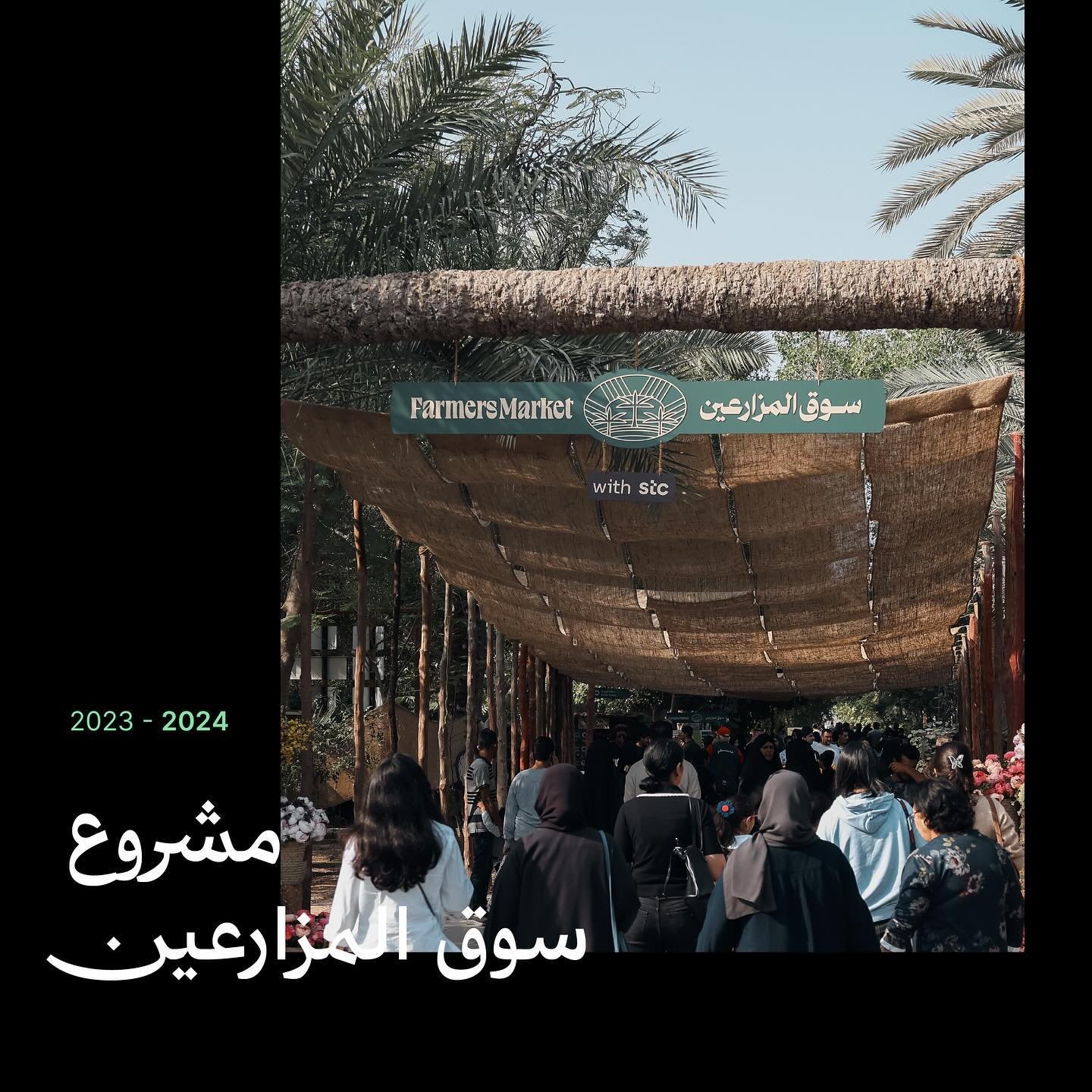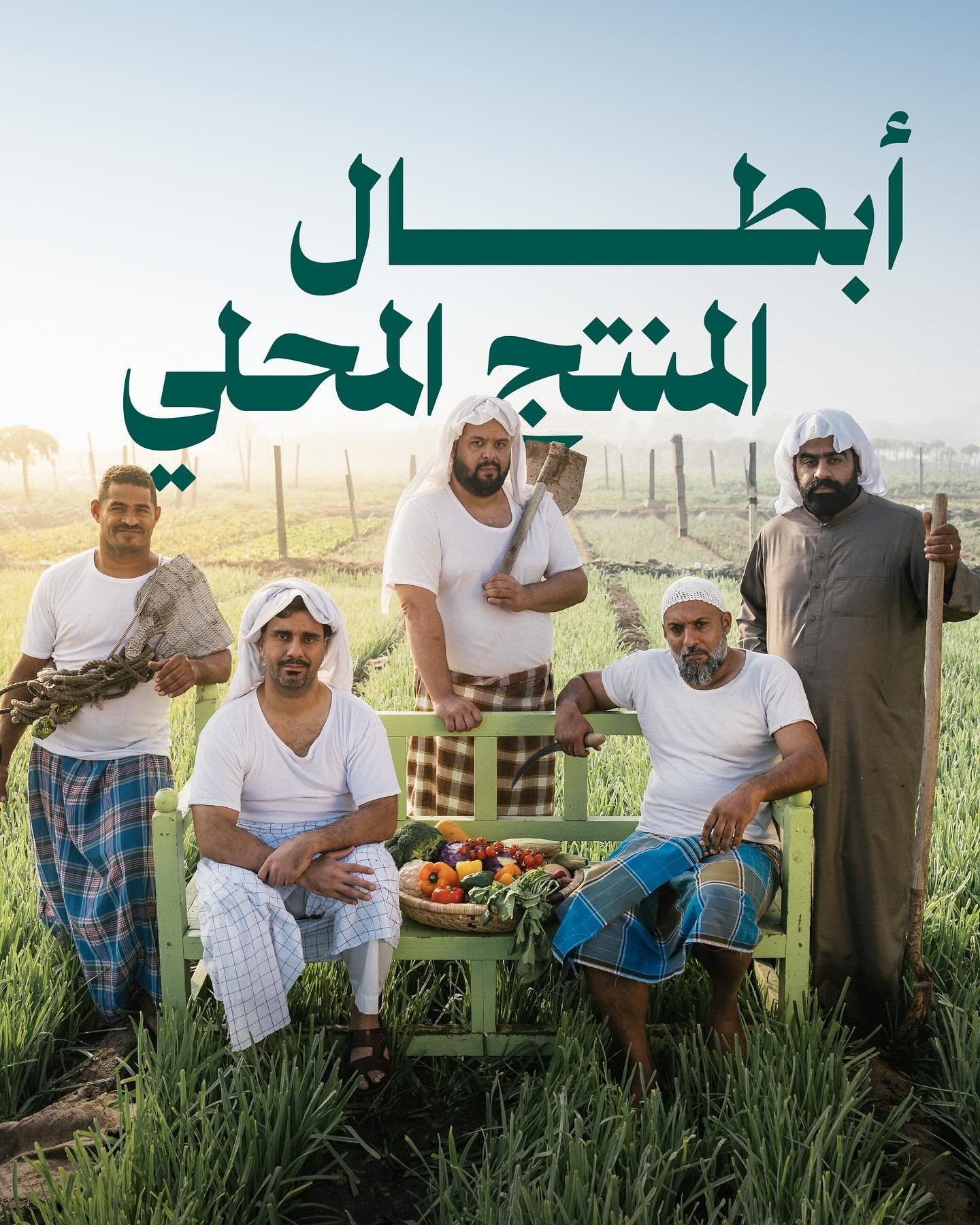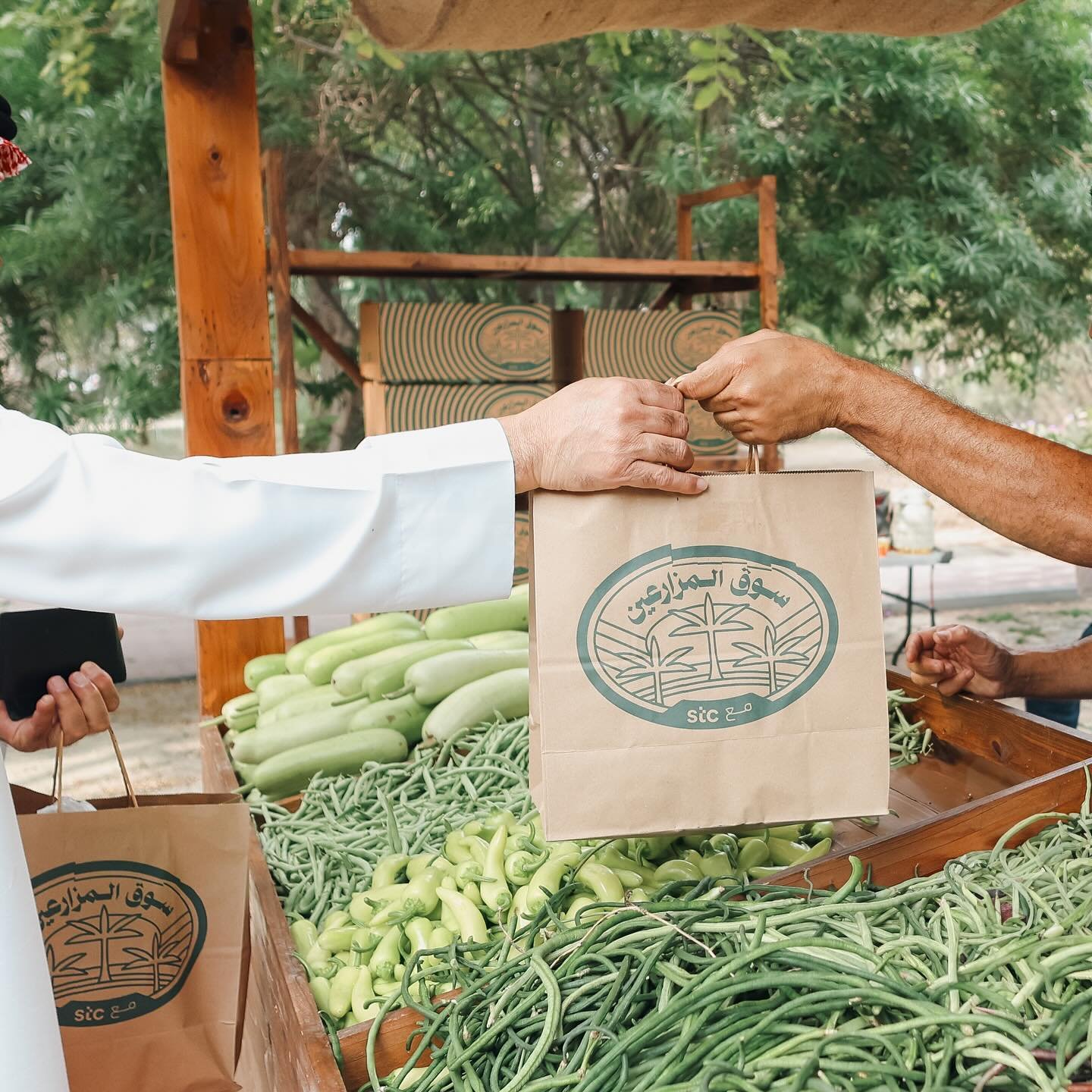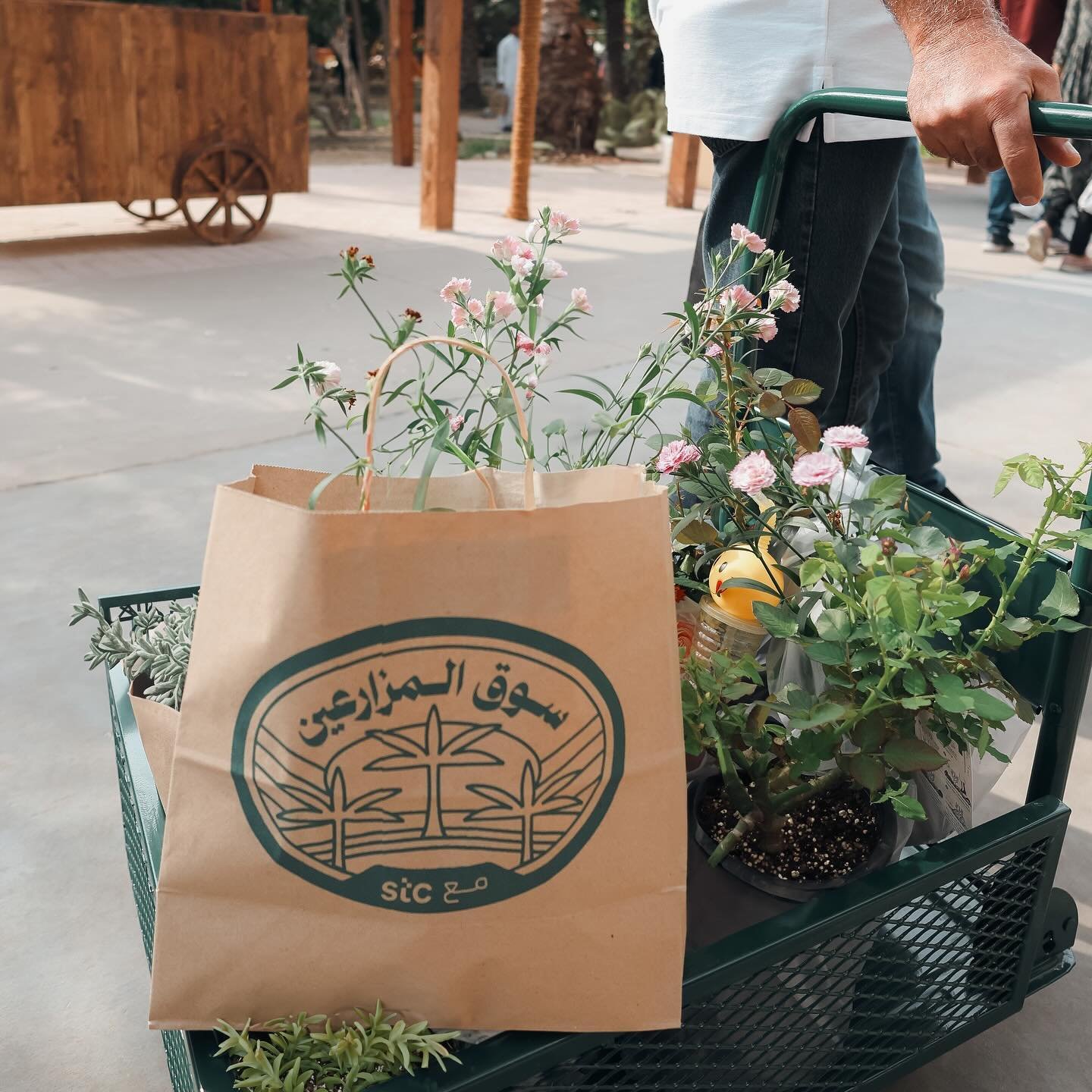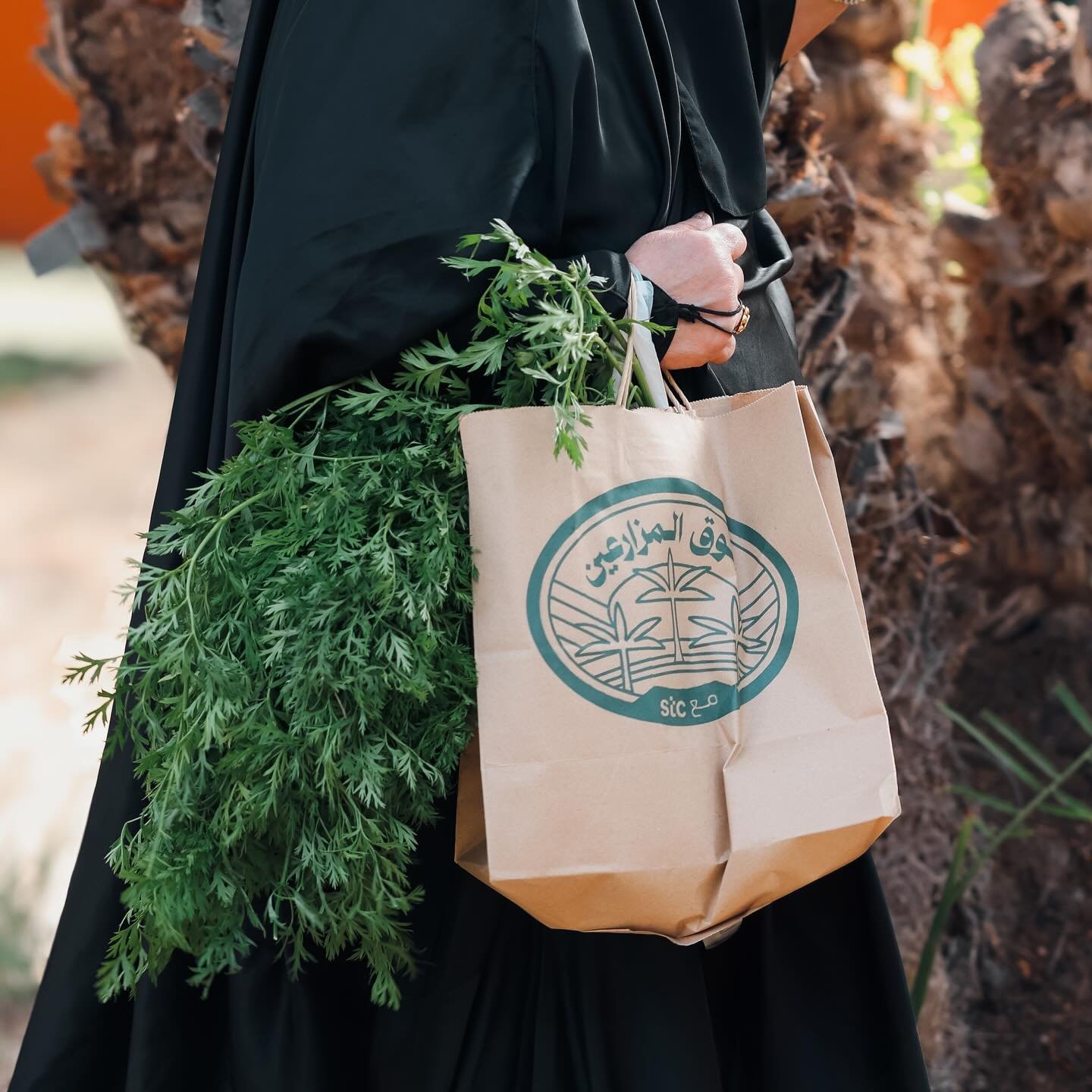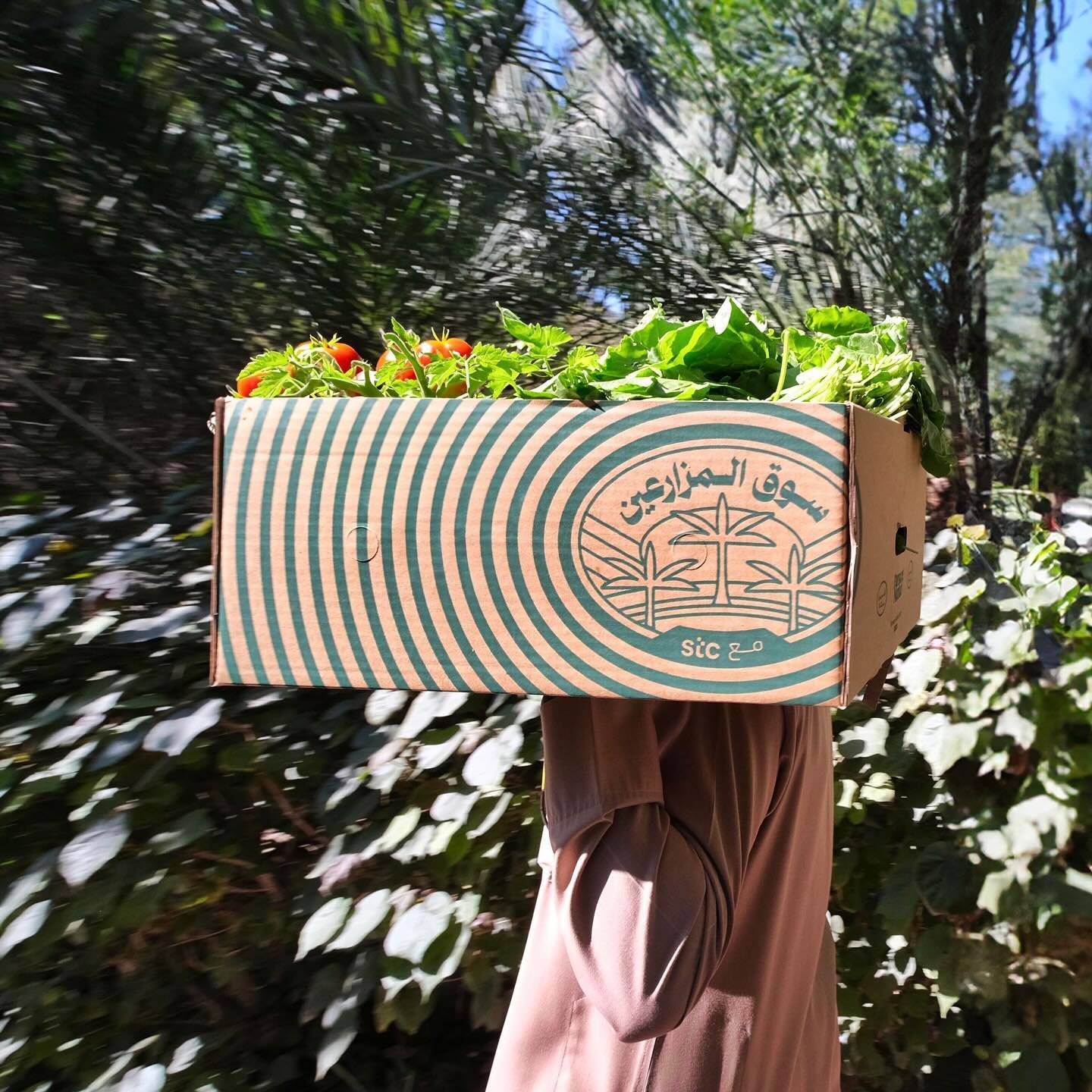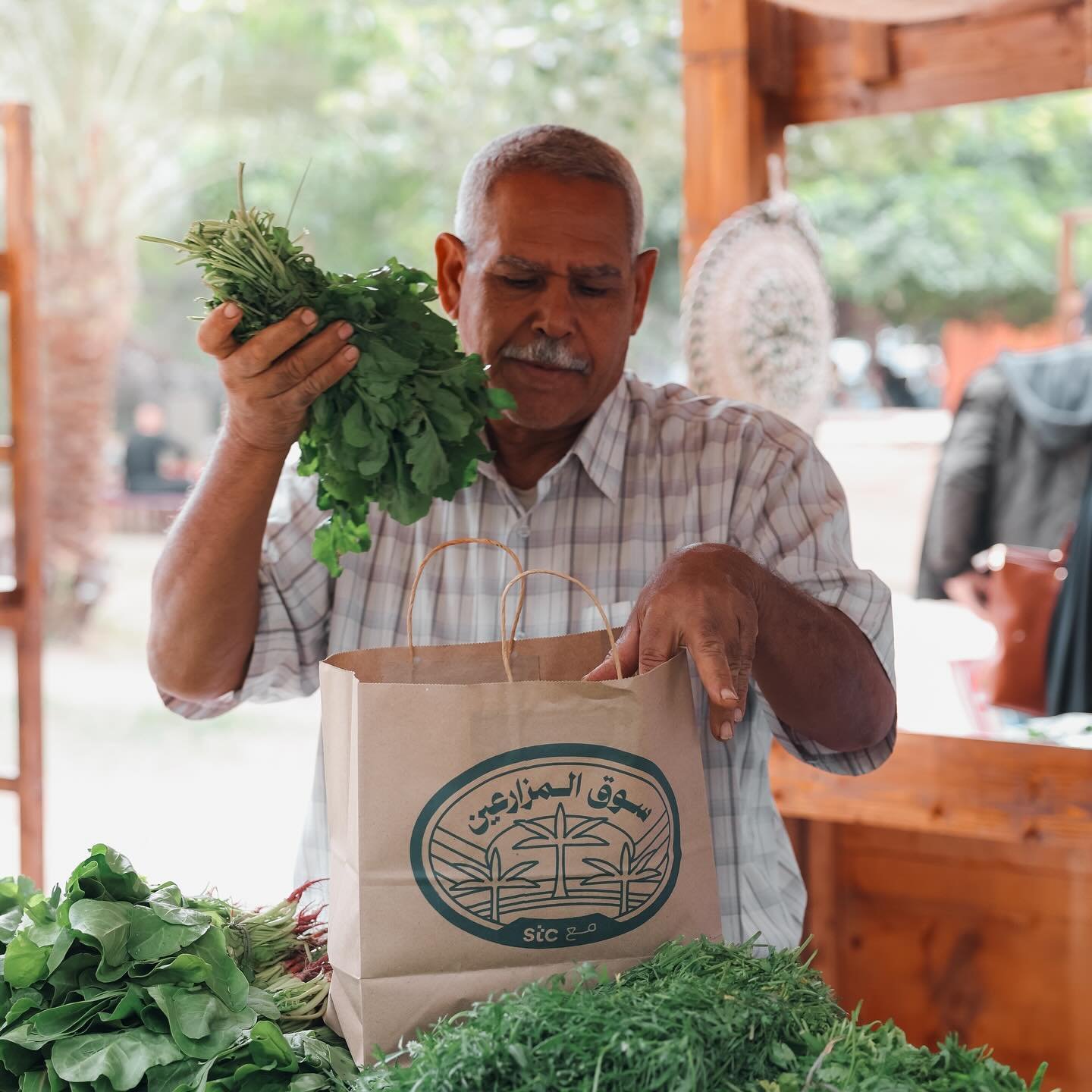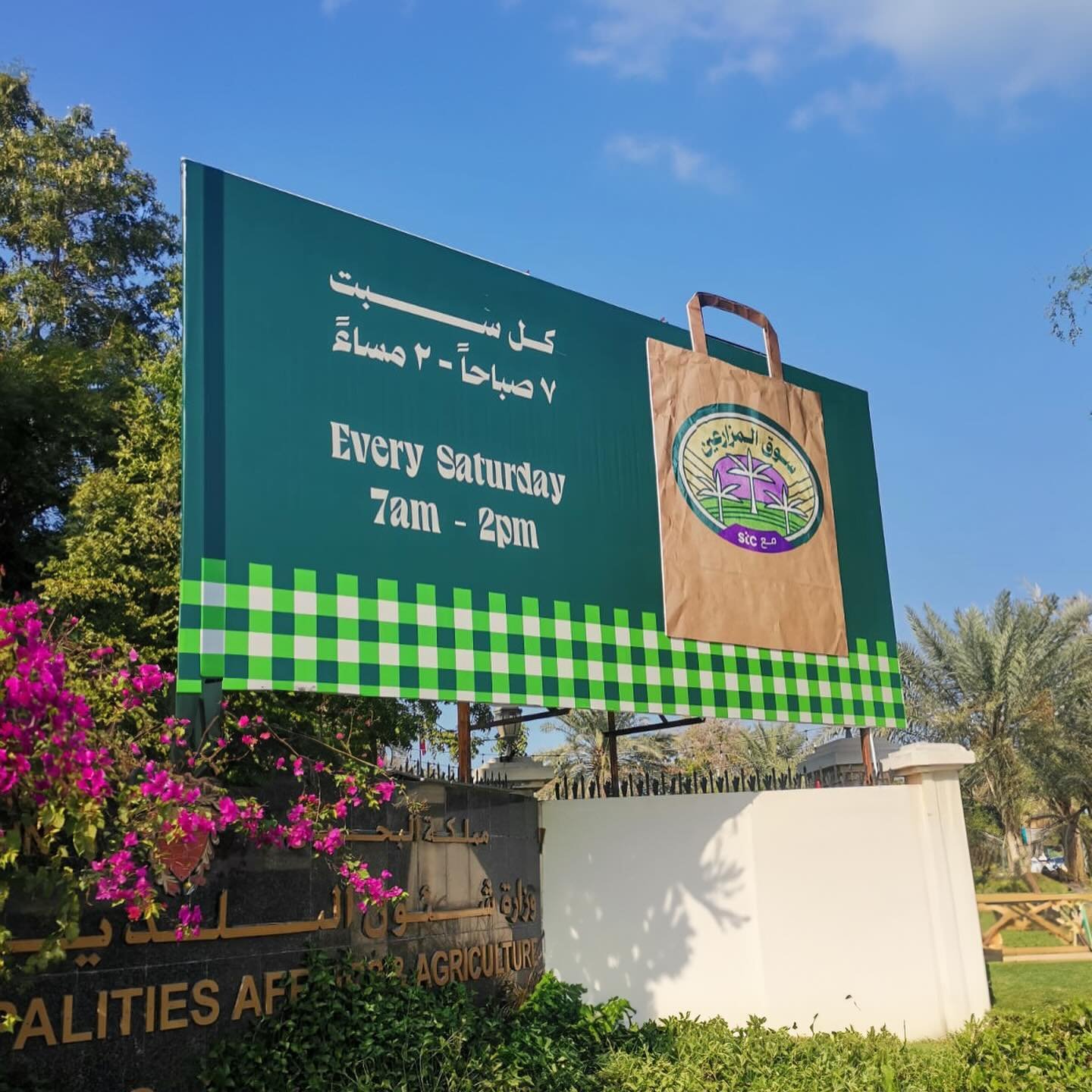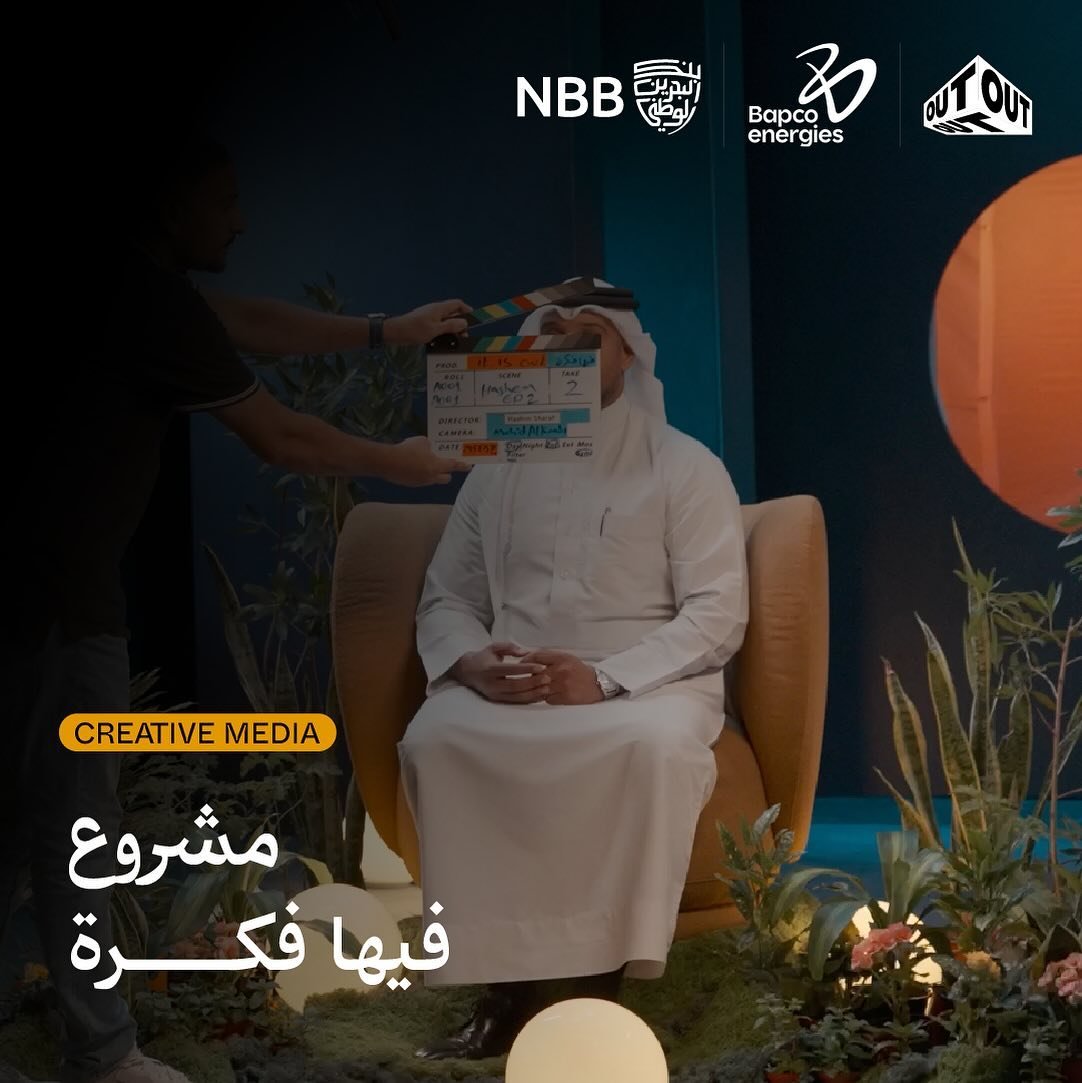
استخدام خط سلمي و خط دهب – OUT CREATIVE STUDIO
سلمى هو خط حديث مستوحى من أسلوب النسخ المَصري. يتميز عن الخطوط التقليدية بتباينه العالي والروابط الجديدة بين الحروف، مما يخلق جمالية ملفتة للنظر تجعل أي نص يبرز. خطوطه العريضة وجاذبيته الخالدة تجعل من سلمى خيارًا مثاليًا للعناوين والطباعة العرضية، بالإضافة إلى مشاريع التصميم الأخرى. يتوفر بخمسة أوزان تتراوح من الخفيف إلى الأسود .
دهب هو خط عربي حديث صممه احمد ظاظا . التصميم مستوحي من اسلوب النسخ . و النتيجة هي مزيج يجمع بين النسب الحديثة و النصوص العربية الكلاسيكية . انها مناسبة للعلامات التجارية و التحرير التعبيئة و الاعلان . دهب عربي يتميز بخمسة اوزان من العادي الي الاسود .